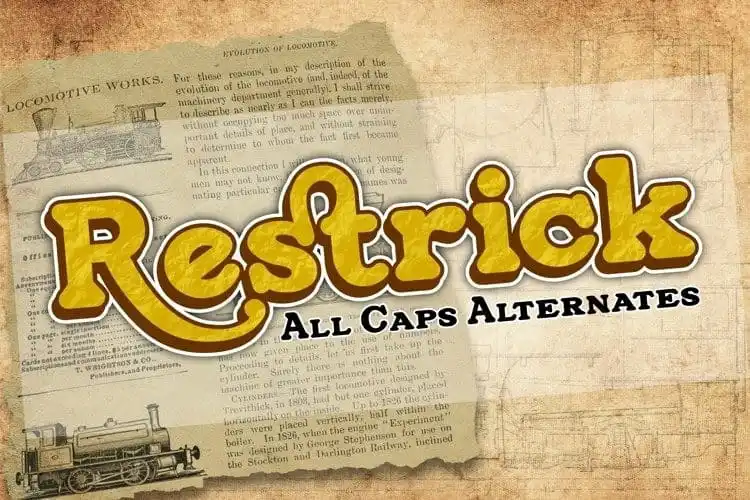
Restrick Display Font
A Restrick Display Font é uma escolha perfeita para quem busca um estilo atraente e moderno que brinca com curvas elegantes. Desenvolvida pela ZetDesign, esta fonte apresenta detalhes finos como suaves alternativas de sinos e combina cada caractere em ótimas referências ao tipo gráfico. Suas bordas arredondadas oferecem flexibilidade para uso em várias plataformas de mídia, tornando-a ideal para headlines nas revistas, cartazes e jornais. Este fonte está disponível tanto na versão regular quanto na itálica, fazendo dela uma opção versátil para diversos cenários. Com sua riqueza de detalhes e estilo único, a Restrick Display Font é perfeita para destacar seu design em qualquer aplicação gráfica.